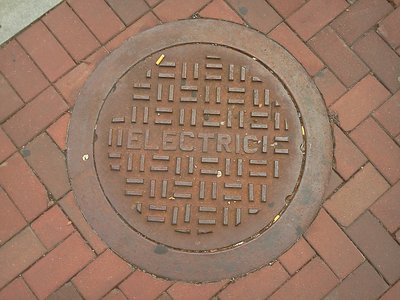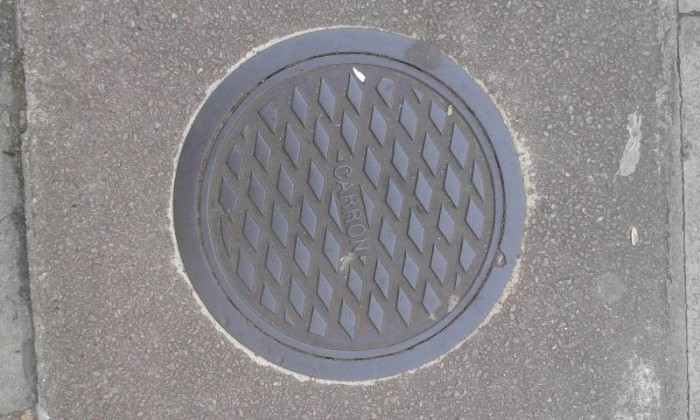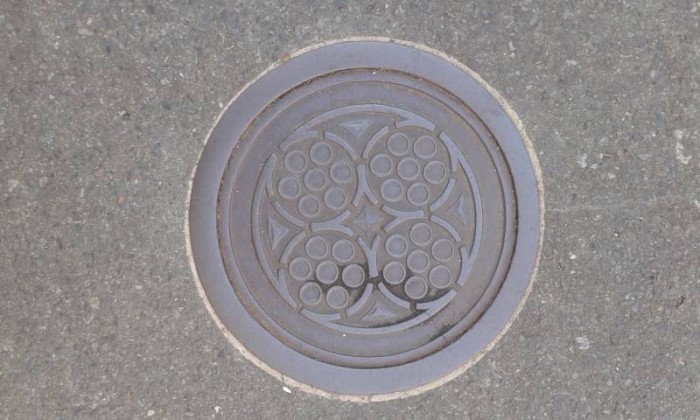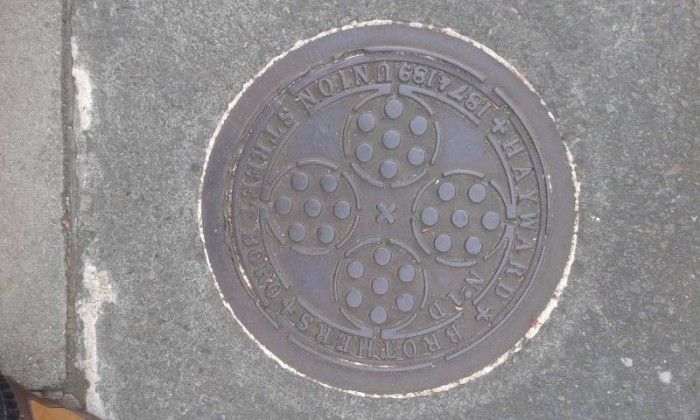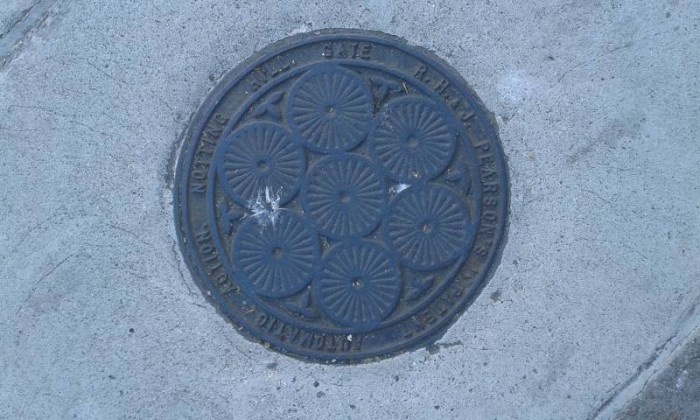
… Kaiser Wilhelm II. besuchte Hamburg und wollte auf einem Siel mit dem Boot fahren um die modernen Anlagen zu besichtigen. …
In Köln wollte er auch in den Untergrund, dazu wurde extra ein Kronleuchtersaal in die Kanalisation gebaut. Übrigens umsonst, weil der Kaiser dann doch keine Lust hatte hinunterzusteigen ;-)
London, Cosway Street.
Wenn ich die Hayward-Spur verfolge, sind das wohl coal plates, also Abdeckungen zum Kohlenkeller, durch deren Öffnungen dann die Kohle gekippt wurde. In Deutschland wurde das ja meist durch die Kellerfenster geschüttet oder, soweit baulich nicht anders möglich, in den Keller getragen.
Ja, darum auch so viele, einer neben dem anderen: halt vor jedem Haus einer!  :nicken:
Wie ist es mit diesem? Der kommt von Blenheim Palace, dem Geburtshaus von Winston Churchill. Hat mir gefallen!
Hier jetzt endlich die gut zwei Dutzend Deckel, die ich im Oktober auf dem Zentralcampus der Penn State University mitnehmen konnte. Zwar nur mit der Telefonkamera, aber es hat trotzdem ein wenig Überwindung gekostet, das vor jeweils ca. 500 Zuschauerinnen durchzuziehen, die auf dem weitläufigen, aber sehr geschäftigen Campus von Veranstaltung zu Veranstaltung eilten. Besonders einfallsreich gestaltet finde ich die Deckel, ganz USA-typisch, nicht unbedingt, aber die Heterogenität hat mich auf dem Gelände einer einzigen Organisation doch etwas erstaunt. Hier sind zwei Beispiele, den Rests gibts auf der oben verlinkten Seite. Dort gibt es auch einen Link mit einem ZIP-Archiv aller Bilder, extra für Pachulke. :huhu:
… aber es hat trotzdem ein wenig Überwindung gekostet, das vor jeweils ca. 500 Zuschauerinnen durchzuziehen, die auf dem weitläufigen, aber sehr geschäftigen Campus von Veranstaltung zu Veranstaltung eilten.
Die Heterogenität ist sicherlich pragmatischer Natur.
… und praktischer: Es hat schon eine gewisse Berechtigung, den Fernwärmeschacht mit »Steam« und die Stromschläuche mit »Electric« zu kennzeichnen. Mit »Vent«, »Sewer« und »Telephone«/»Communication« haben wir hier schon mindestens fünf verschiedene Versorgungssysteme. Als ich neulich von ca. neun verschiedenen Unternehmen Schachtscheine für mein Grundstück eingeholt habe, wäre ich auch nicht böse gewesen, wenn das alles so schön systematisch und erkennbar eingedeckelt gewesen wäre.
Das sind Genehmigungen von Versorgungsunternehmen (Gas, Wasser, Telekommunikation etc.) die theoretisch auf einem Grundstück Versorgungsleitungen liegen haben könnten und allein wissen, wo. Es hat z. B. schon einen gewissen Sinn, zu wissen, wo eine Gasleitung liegt, ehe man ein Bohrung ins Erdreich einbringt, es könnte sonst möglicherweise die letzte sein. Das ganze Prozedere, eine lange Liste potentieller Unternehmen abzufragen, ist freilich höchst ineffizient. Da wäre ein zentrales Kataster hilfreich, in das alle solche Leitungen einzutragen wären. Gibt es aber nicht, und es gibt hier einige Versorger, die schlicht selbst nicht wissen, was wo liegt, weil sie von DDR-Vorgängern undokumentierte Schächte »geerbt« haben. Aber das betrifft dann wenigstens nicht solch sensible Medien wie Gas.
:trost:
Man wird dafür aber mitunter auch in interessante Gespräche verwickelt.
Ist mir nicht passiert. :-? Ich habe nur ein paar skeptische Blicke geerntet. Vielleicht liegt es ja daran, dass die US-Deckel außer Hardcorefans wirklich kaum jemandem fotografierwürdig erscheinen.
Es hat schon eine gewisse Berechtigung, den Fernwärmeschacht mit »Steam« und die Stromschläuche mit »Electric« zu kennzeichnen.ennbar eingedeckelt gewesen wäre.
Ja klar, aber das meine ich nicht. Ich meine die Heterogenität des Deckeldesigns. Es gibt auf dem einen Campus (also bei einem Auftraggeber für Versorgungsschächte) ja mindestens 11 verschiedene Grunddesigns für Deckel – und aus so vielen verschiedenen Jahrzehnten stammen die auch nicht.
Als ich neulich von ca. neun verschiedenen Unternehmen Schachtscheine für mein Grundstück eingeholt habe, wäre ich auch nicht böse gewesen, wenn das alles so schön systematisch und erkennbar eingedeckelt gewesen wäre.
Das ist bei uns (in den USA) übrigens sehr praktisch gelöst. Bevor ich im Vorgarten Bäume pflanzte, rief ich eine kostenlose Telefonnummer an – und am nächsten Tag hatten alle Versorgungsunternehmen den Verlauf ihrer Leitungen mit farbcodierter Sprayfarbe, die innerhalb von ein paar Tagen wieder verschwindet, auf Straße, Einfahrt und Rasen gesprüht.